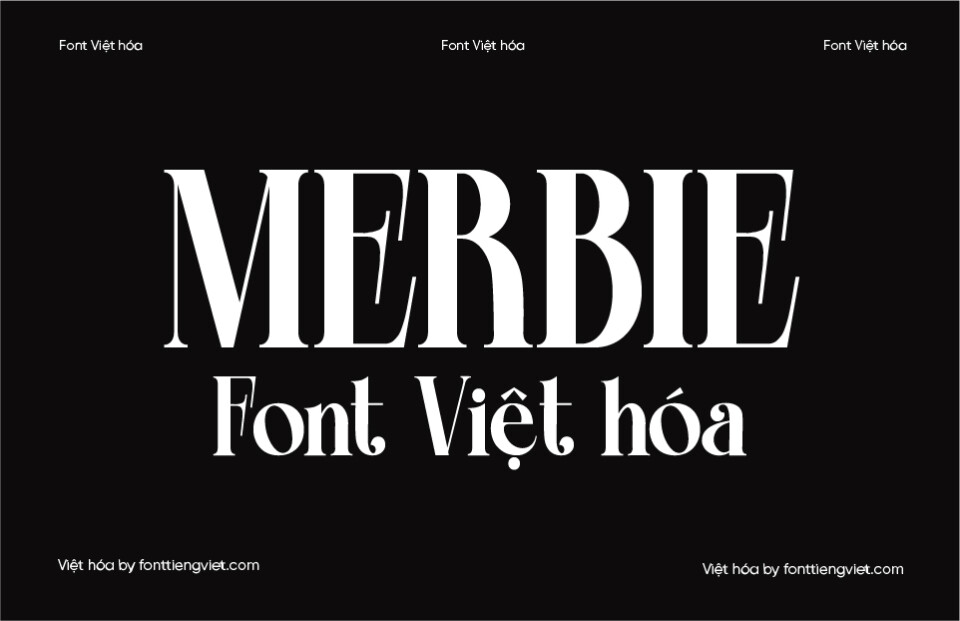
Font Việt hóa 1FTV VIP Merbie
Font Việt hóa 1FTV VIP Merbie – Bộ font chữ thiết kế hiện đại và sang trọng cho giáo dục
Giới thiệu về Font Việt hóa 1FTV VIP Merbie
Trong thế giới đồ họa hiện đại, việc tìm kiếm một bộ Font Miễn Phí chất lượng cao là ưu tiên hàng đầu của các nhà thiết kế và giáo viên. Font Việt hóa 1FTV VIP Merbie nổi lên như một lựa chọn hoàn hảo nhờ sự kết hợp giữa nét chữ thanh thoát và tính ứng dụng cao. Được tinh chỉnh kỹ lưỡng về dấu tiếng Việt, bộ font này mang lại sự chuyên nghiệp tuyệt đối cho mọi sản phẩm truyền thông học đường cũng như các dự án sáng tạo cá nhân.
Tại sao nên chọn Font Việt hóa 1FTV VIP Merbie?
Đặc điểm nổi bật của bộ font này chính là cấu trúc hình học hiện đại nhưng không kém phần mềm mại. Với độ dày nét cân đối, nó giúp văn bản trở nên dễ đọc trên cả màn hình kỹ thuật số và các bản in truyền thống. Điều này đặc biệt quan trọng trong môi trường giáo dục, nơi mà sự rõ ràng và tính thẩm mỹ cần song hành để thu hút sự chú ý của học sinh.
Ứng dụng Font Việt hóa 1FTV VIP Merbie trong thực tế
Bộ font này cực kỳ linh hoạt trong nhiều tình huống thiết kế khác nhau. Bạn có thể sử dụng nó để làm tiêu đề bài giảng, thiết kế poster sự kiện trường học hoặc trình bày slide thuyết trình. Khả năng hiển thị sắc nét của font giúp truyền tải nội dung một cách mạch lạc, tạo ấn tượng mạnh mẽ với người xem ngay từ cái nhìn đầu tiên.
Kết luận về bộ font chữ độc đáo